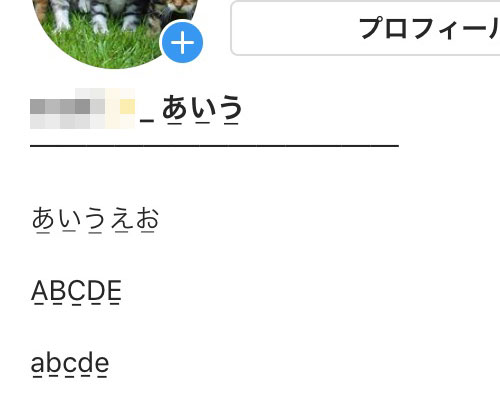
インスタで文字にアンダーラインを入れる方法!文字を目立たせたい時に便利です
インスタでプロフィールや名前の文字にアンダーラインを入れる方法を知っていますか?
文字にアンダーラインを付けると普通の文字と違って少し目立つ文字になります。
実際にアンダーラインを入れた文字がどういう見え方になるのか試してみました。
あ̲い̲う̲え̲お̲
A̲B̲C̲D̲E̲
a̲b̲c̲d̲e̲
このようにひらがなや英語のアルファベットにもアンダーラインを入れる事ができます。
ただし、通常の文字変換ではアンダーラインの文字を入力する事はできません。
そこで、このページではインスタの文字にアンダーラインを入れる方法について解説します。
インスタで文字にアンダーラインを入れる方法
コピーした文字はそのままインスタのプロフィールや名前に貼り付けするとアンダーラインの文字をそのまま使う事ができます。
英語のアンダーライン文字は通常の文字では変換できない特殊文字なので上記のツールを使って特殊文字を作成しましょう。
アンダーラインのデザインバリエーション
アンダーラインはシンプルな一本線だけでなくさまざまなデザインを取り入れることで投稿の印象を大きく変えられます。
例えば手書き風のゆるい波線を使うとカジュアルな雰囲気になり点線を使うとスタイリッシュな印象になります。
また二重線や破線を活用すると他のテキストと差別化しやすくなります。
さらにハートや星矢印などの記号を交えたアンダーラインを加えることで可愛らしいデザインに仕上げることもできます。
こうしたアンダーラインを活用するとフォロワーの目を引きやすくなるでしょう。
ストーリーでのアンダーライン活用法
インスタのストーリーではアンダーラインを活用することで特定のメッセージを強調したりテキストを目立たせたりすることができます。
手書きツールでサッと引くだけでも印象が変わりますがペンの種類を変えることでより個性的な表現が可能です。
例えば「蛍光ペンツール」を使うと文字の背景に透け感のあるアンダーラインを加えられ目立ちやすくなります。
また「マーカー」や「グロー」などのペンを活用するとよりポップな印象に仕上がります。
ストーリーでは短時間で視認性を高めることが大切なのでシンプルかつインパクトのあるアンダーラインを使うのがおすすめです。
ユーザーネームにアンダーライン文字は使えないので注意
インスタではユーザーネームと名前が別々で設定できます。
ユーザーネームは英数字やアンダーラインを使って設定できますが、ここで解説した『アンダーライン文字』は使う事ができません。
アンダーライン文字は特殊文字なので通常の英数字として認識されないようです。
プロフィールの自己紹介や名前の部分には使えるので、もしアンダーライン文字を使用する時は注意しましょう。
下線が表示されない原因
アンダーライン文字をコピペしたのに表示されない場合いくつか原因が考えられます。
代表的なのはフォント互換性の問題で端末やOSによっては特殊文字が正しく表示されないことがあります。
またインスタの入力欄によっては自動変換されてしまい下線が消えるケースもあります。
対策としては別の文字生成ツールを試す投稿前にプレビューで確認するなどが有効です。
特にプロフィールは表示崩れが起きやすいので複数端末でチェックしておくと安心でしょう。
画像に文字を入れてアンダーラインをつける方法
インスタで投稿する際文字にアンダーラインを入れる方法としては画像編集アプリを利用するのもおすすめです。
その後「スタイル」画面に進むと「下線」という機能があり好みに合わせて点線や二重線などを選べます。
プロフィール名やキャプションに直接反映することはできませんが画像上に加工して投稿することで強調したい文字やフレーズをより目立たせることが可能です。
ブログ記事やキャンペーン告知などで強調したい言葉にアンダーラインを入れると視覚的に分かりやすくなるでしょう。
アンダーラインの種類を選んで使う
Phontoなどのアプリを使うとアンダーラインのデザインを自由に選べるのが魅力です。
一般的な直線の下線だけでなく「Dash(点線)」「Dot(ドット線)」「Thick(太線)」「Double(二重線)」などさまざまなバリエーションが用意されています。
例えばシンプルに強調したいときは太線カジュアルさを出したいときは点線やドット線を使うと効果的です。
さらに線の色や太さを変えられるため投稿全体のデザインに合わせて調整できます。
アンダーラインをただ引くだけではなく色や種類を組み合わせることで見た目の印象を大きく変えることができるでしょう。
自分の投稿スタイルに合わせて工夫すればオリジナリティのあるデザインに仕上がります。
活用シーンとデザインの工夫
インスタの投稿でアンダーラインを活用する場面は多くあります。
たとえば商品のキャンペーンやセール情報を伝えるとき重要な日付やキーワードに下線を引くと目を引きやすくなります。
また旅行写真やカフェの紹介などではキャプション代わりに写真内に文字を載せその文字に下線をつけることでおしゃれな雰囲気を演出できます。
さらにアンダーラインの色を背景とコーディネートさせたり蛍光ペン風の太線を使ってストーリーで手書き風に仕上げるのもおすすめです。
見せたい部分を効果的に強調しつつ全体のトーンを崩さないように意識することでより洗練された投稿になるでしょう。
工夫次第でデザインの幅が広がるのでぜひ試してみてください。
まとめ
インスタで見かけるアンダーライン文字は特殊文字なのでスマホからそのまま変換する事ができません。
ツールを使えば簡単にコピペできるのでアンダーライン文字を使いたい時にはツールを活用しましょう。
最近では小さいフォントの文字や筆記体の文字なども人気です。